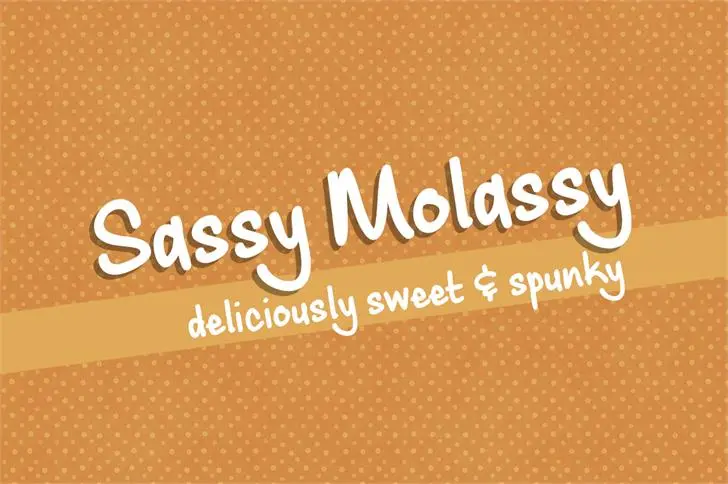
Sassy Molassy font
A fonte Sassy Molassy é uma elegante escolha para designers apaixonados por fontes script. Criada pela Brittney Murphy Design em 2015, essa fonte é perfeita tanto para conteúdo detalhado quanto para headlines impactantes. Feminina e sofisticada, ela adota um toque esperto que a torna uma opção versátil no design gráfico. Seu charme handwritten ganha vida com linhas levemente fortes, o que a torna ideal para aplicar em variados materiais de comunicação, do design editorial aos logotipos e arte publicitária. Suas características fluidas e delicadas fazem dela um excelente recurso para aqueles que buscam uma fonte única capaz de expressar tanto feminilidade quanto espírito jovial no seu trabalho. Não deixe de experimentar Sassy Molassy em sua próxima criação visual para capturar o coração do seu público-alvo com estilo e personalidade.